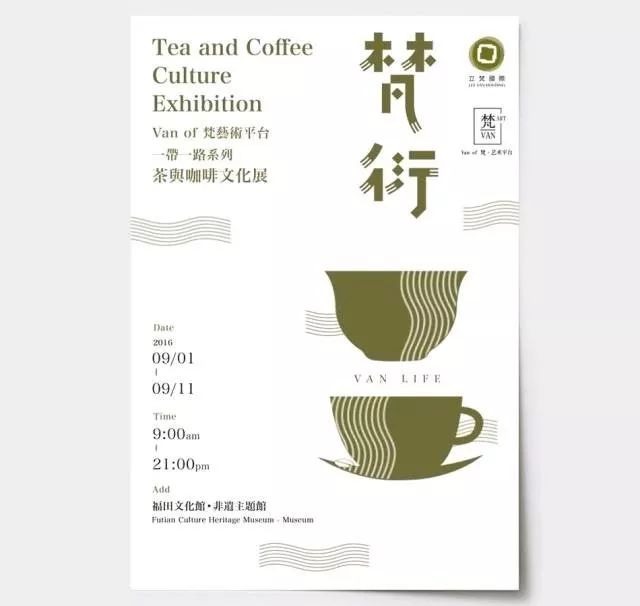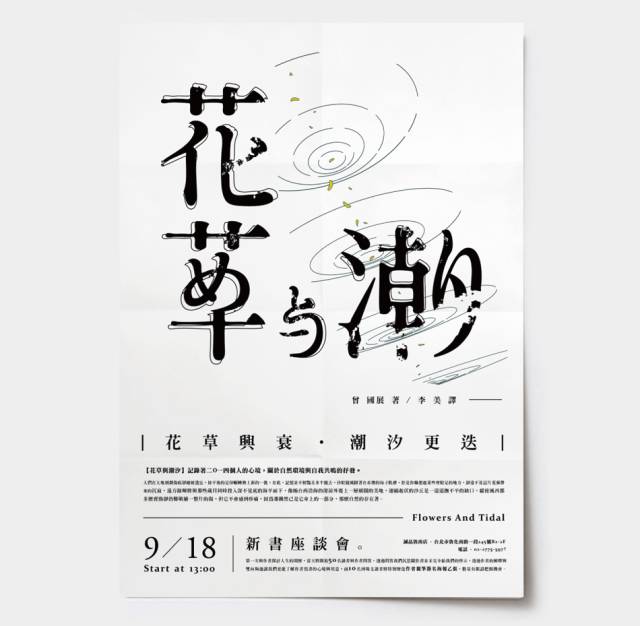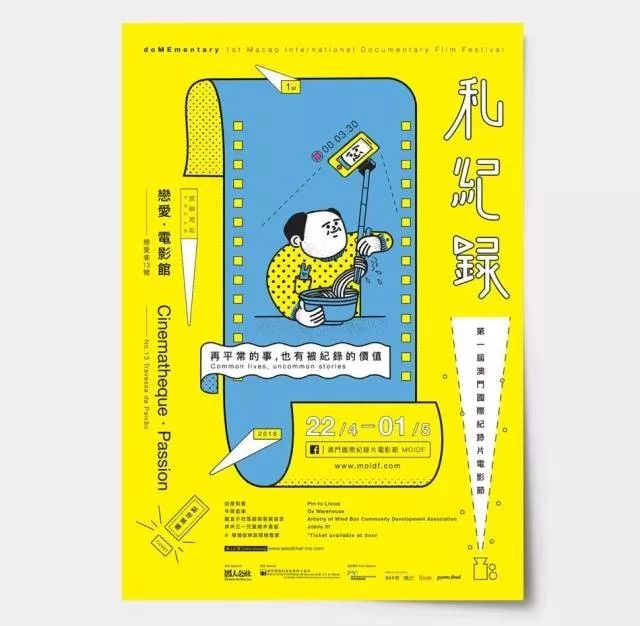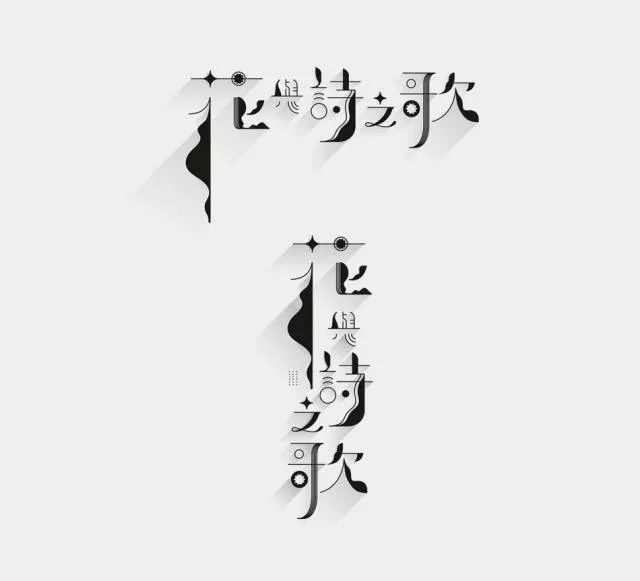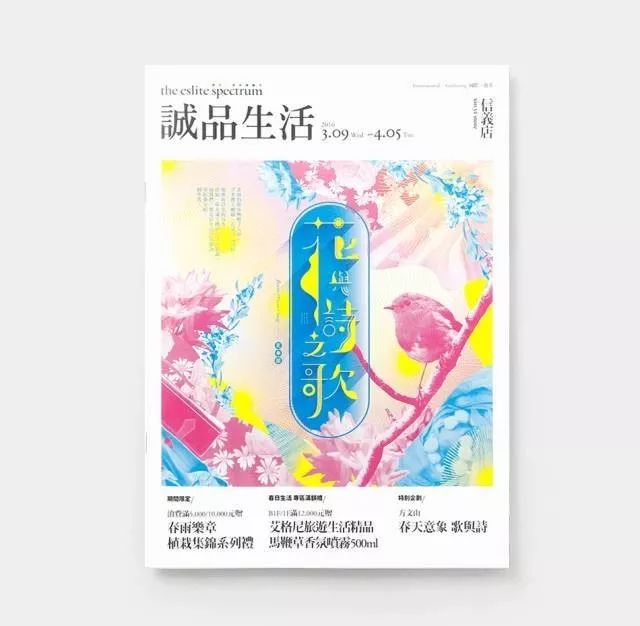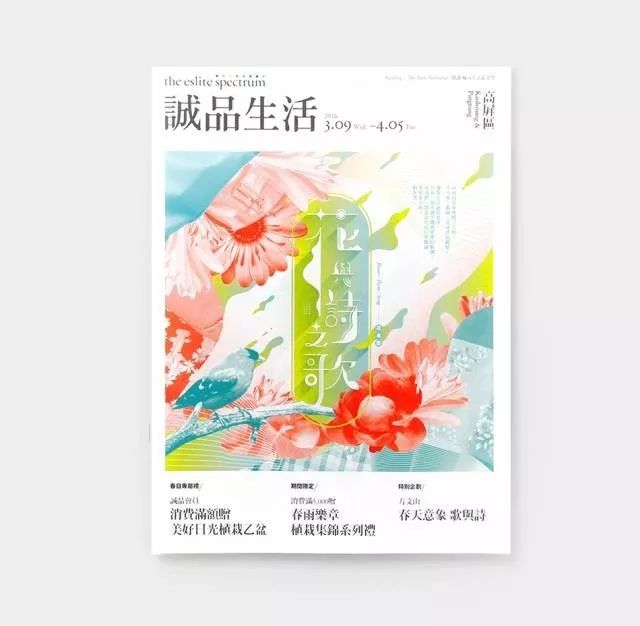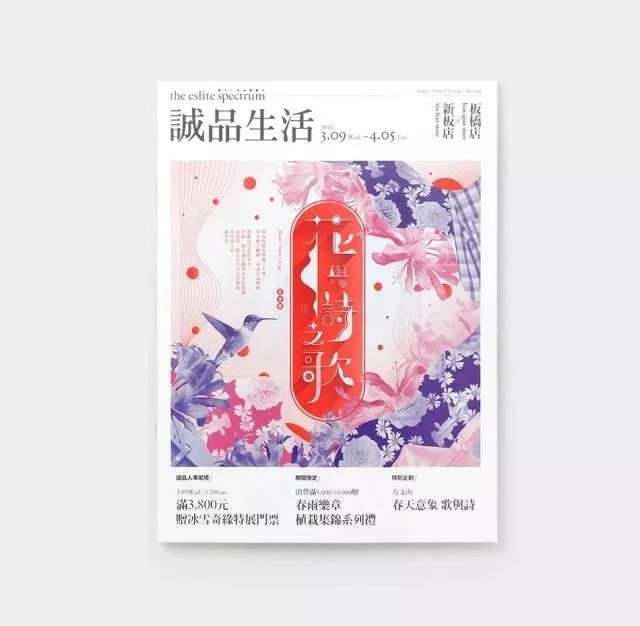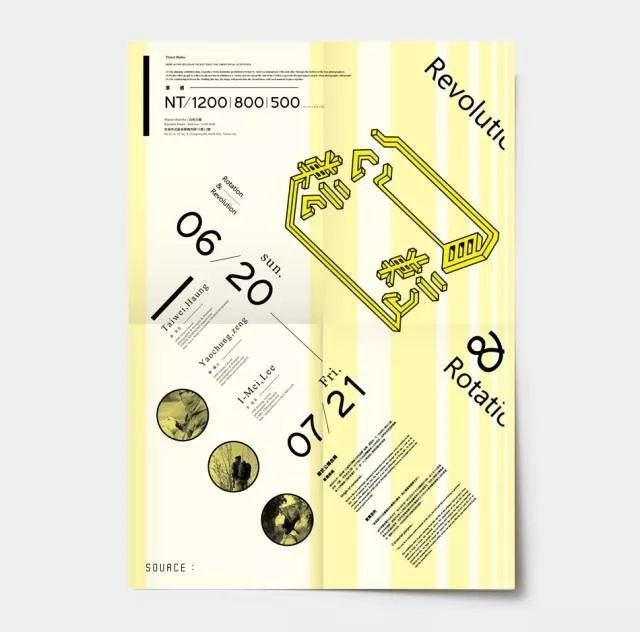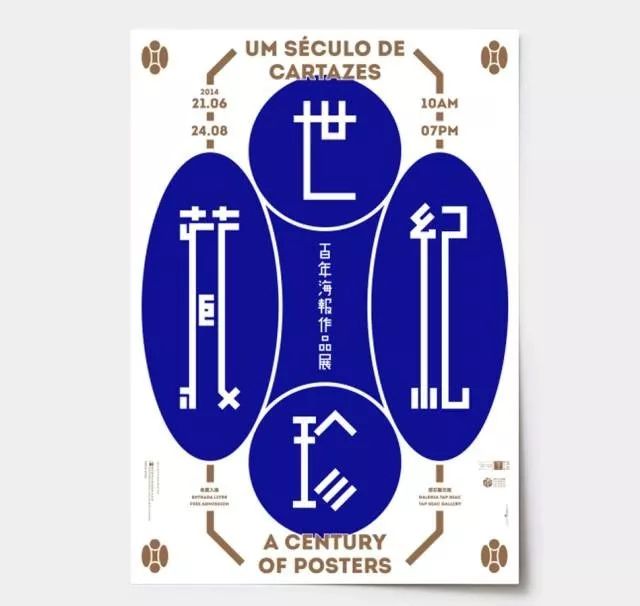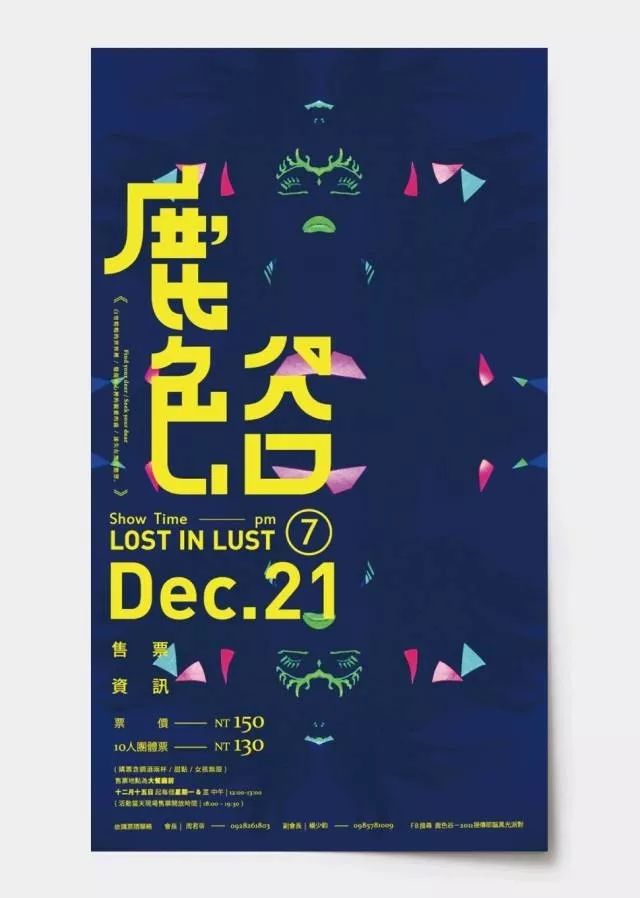
中文海报设计中的字体设计案例
说起海报设计,不得不提字体设计。字体的魔力,可以使版面传递能量和表达情绪,甚至夺人眼球。所以字体是设计中不可或缺的一部分,近些年来也涌现出越来越多的优秀作品,而字体设计可以起到至关重要的作用。下面为大家展示一组海报设计,当中的字体设计也相当精彩和值得借鉴学习的。
《梵衍》
《世纪珍藏》──百年海报作品展
《鹿色谷》
《花草與潮汐》
《私紀錄》──首屆澳門國際紀錄片電影節
《獨立急行》
根據本次企劃概念,將急行特快車作為音樂傳達的媒介
主視覺設計,我們將音樂的傳達與交流以空間穿梭的概念呈現
《花与词之歌》——花傘節
《公轉自轉》
《漢字文化》
《待末影展》